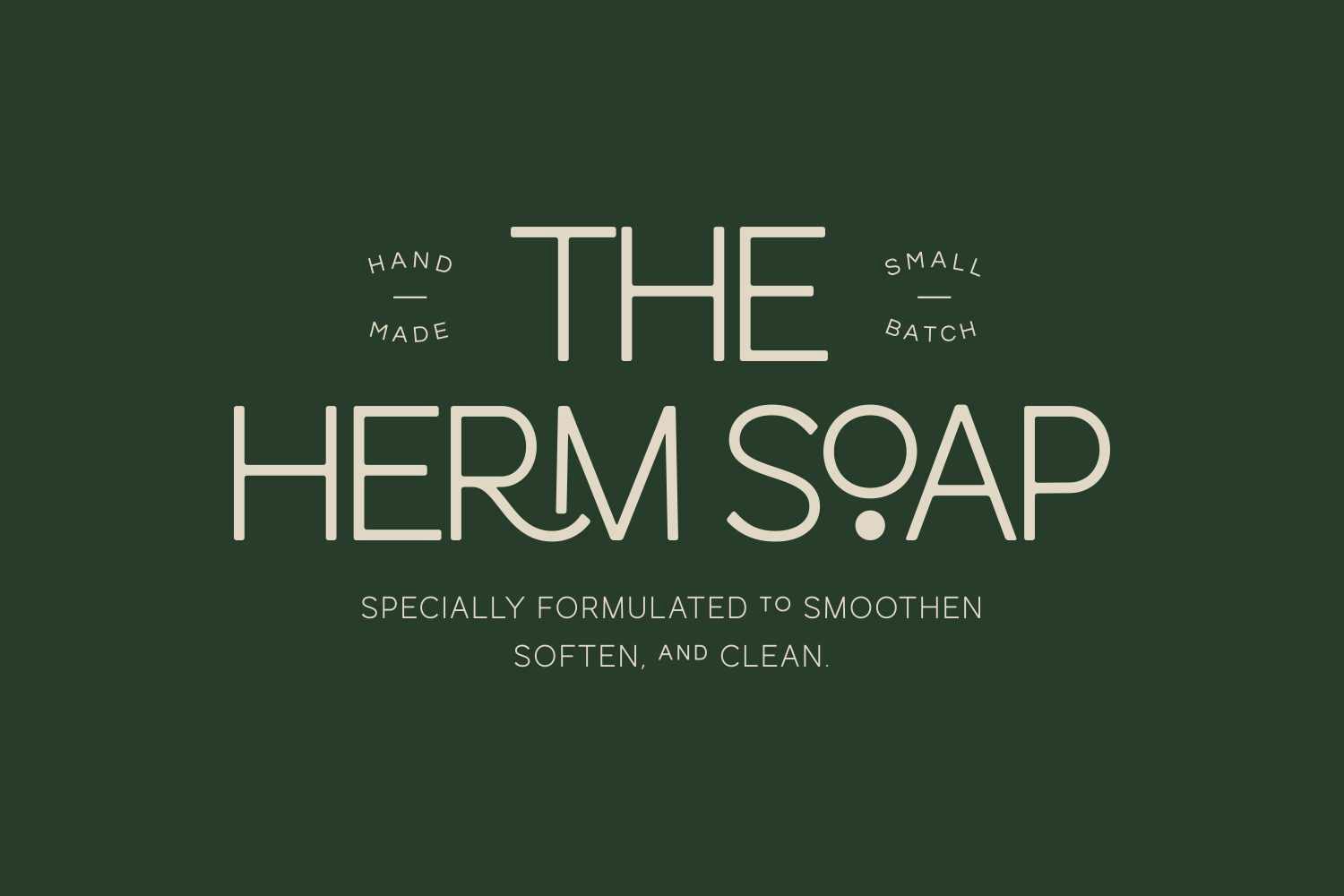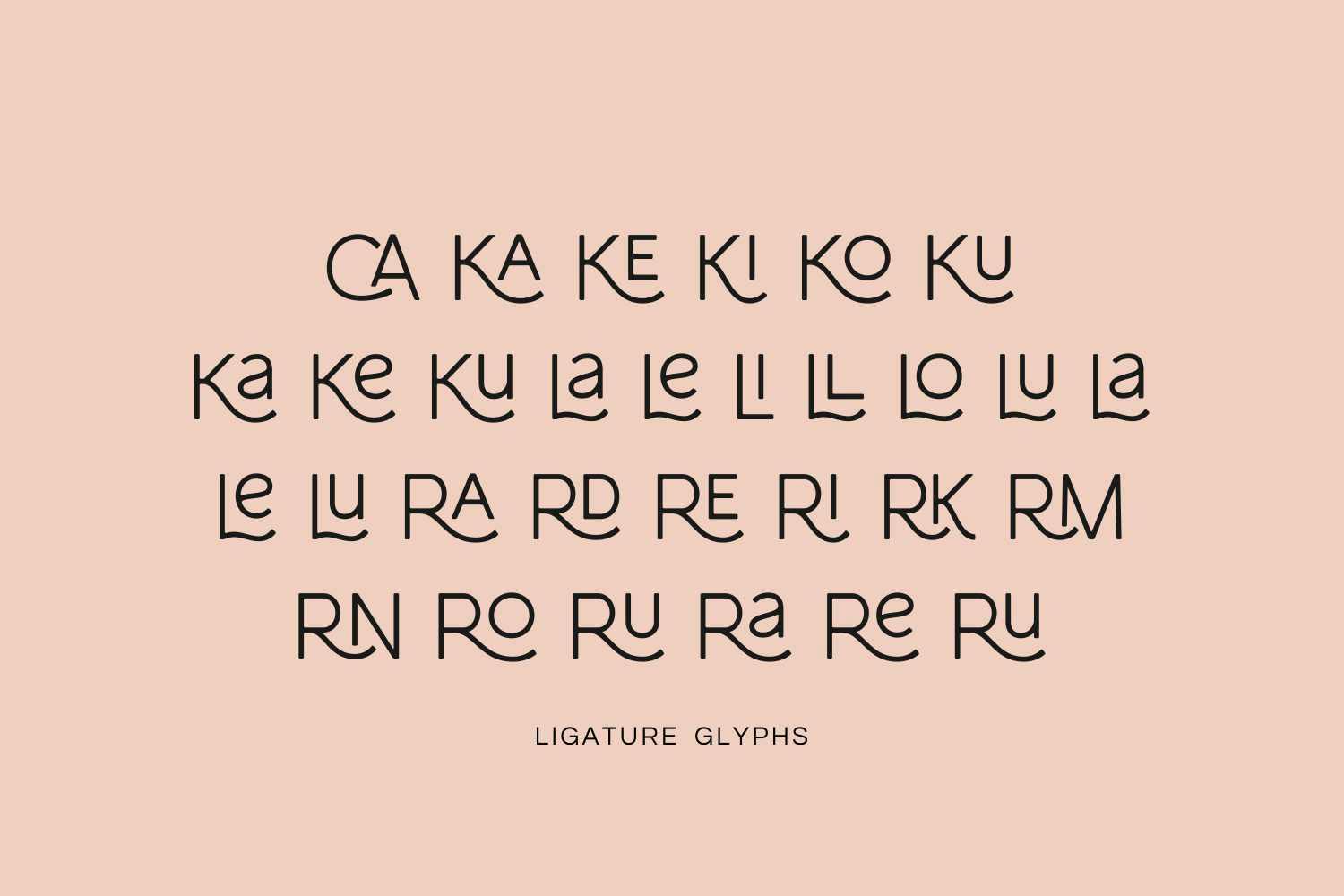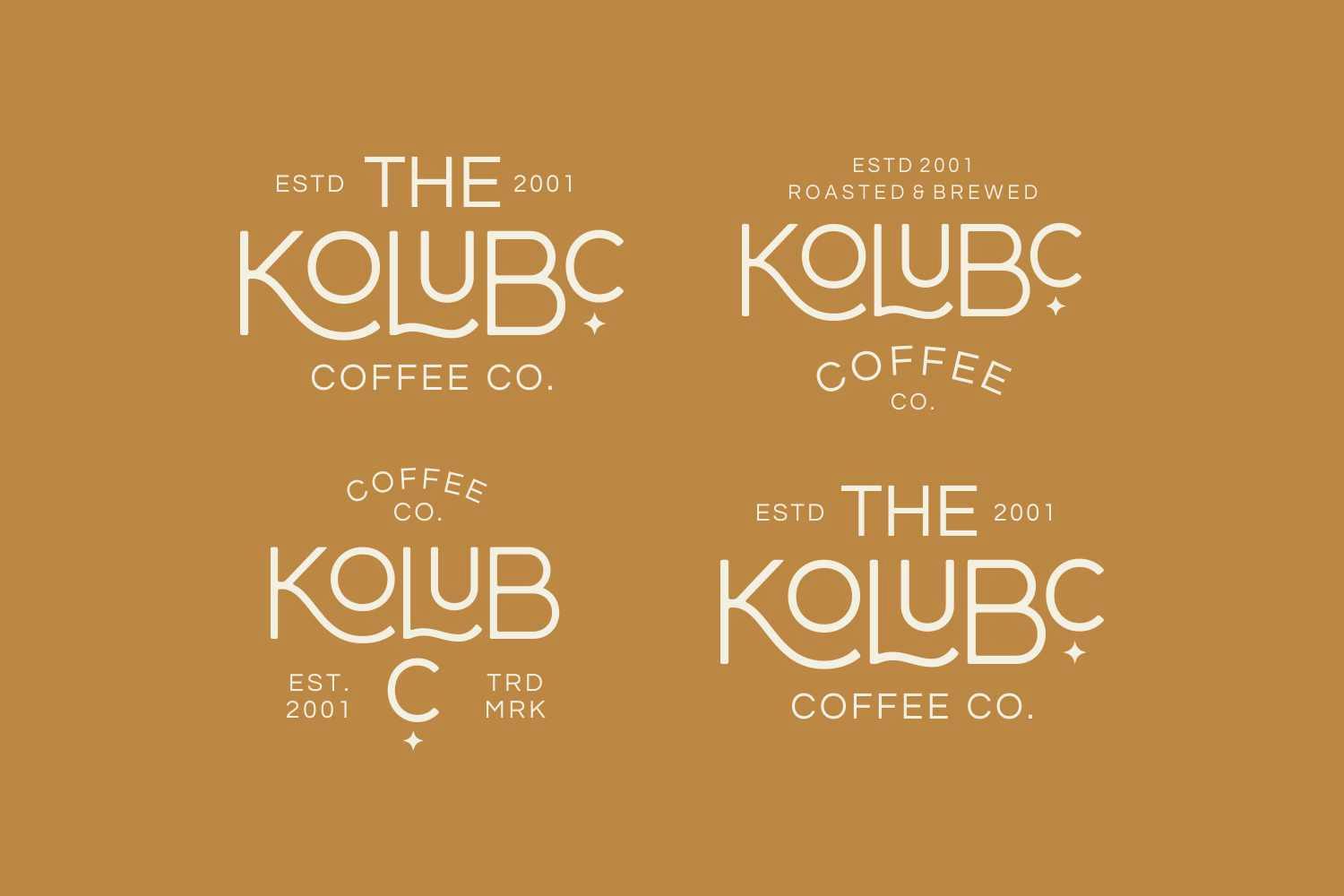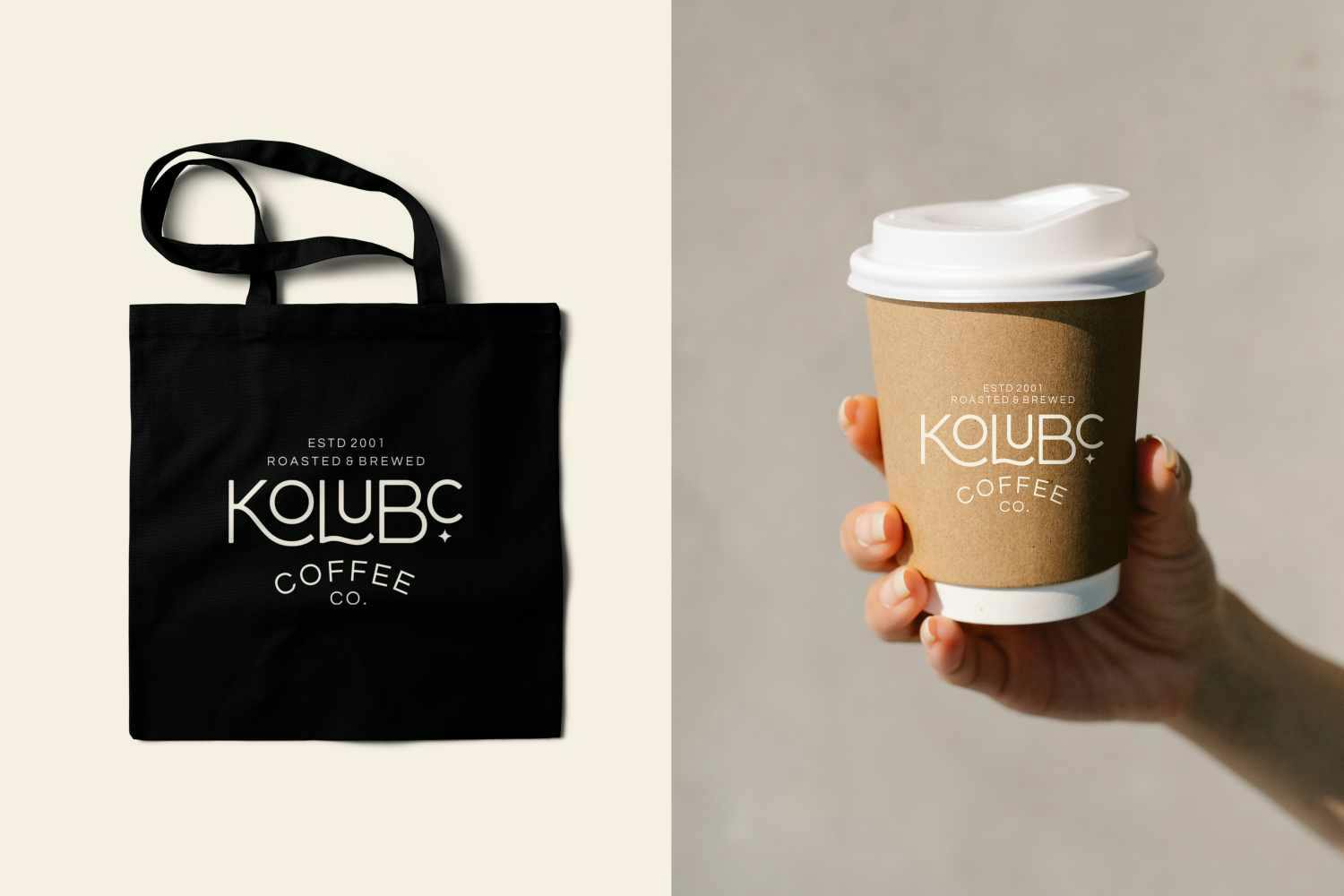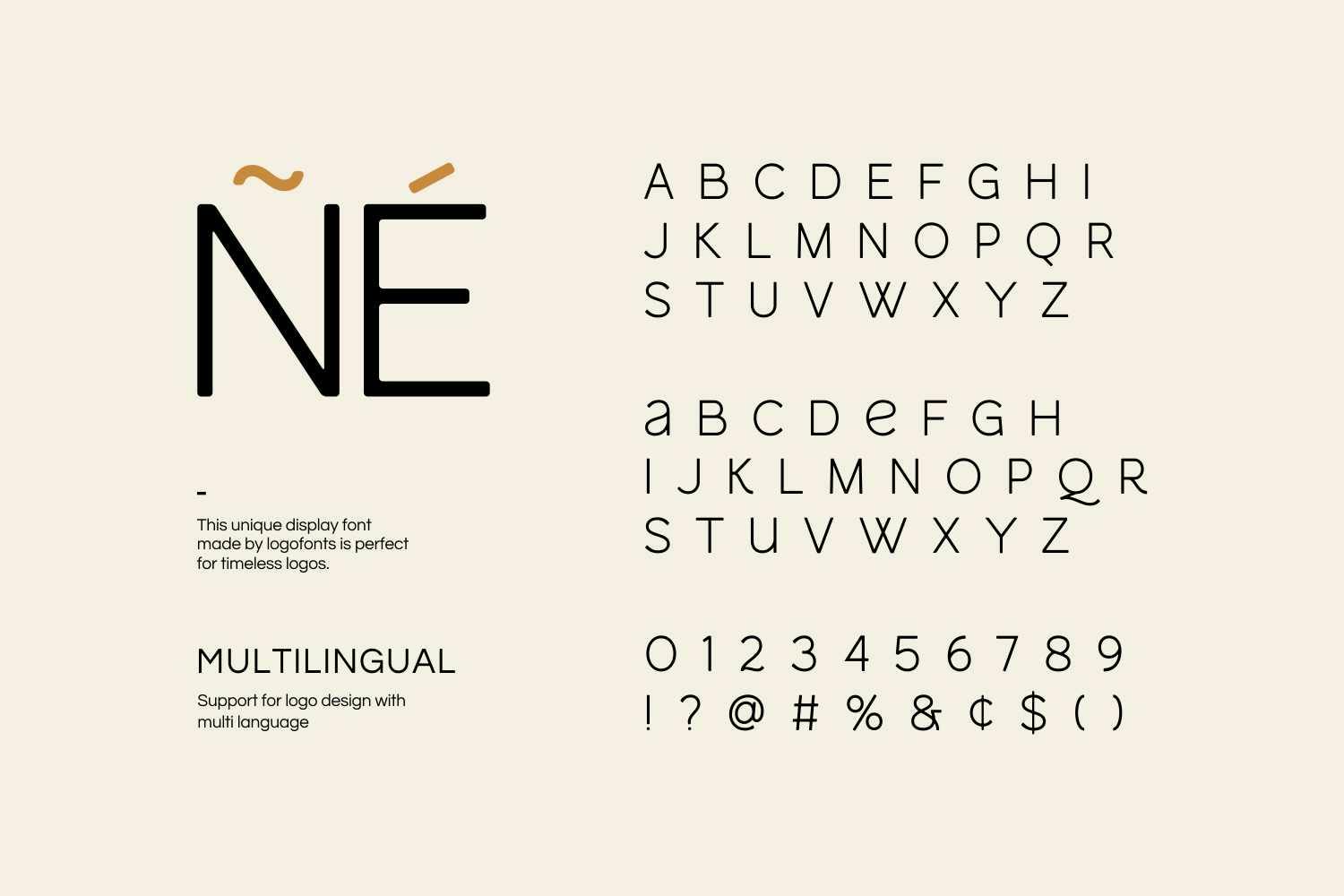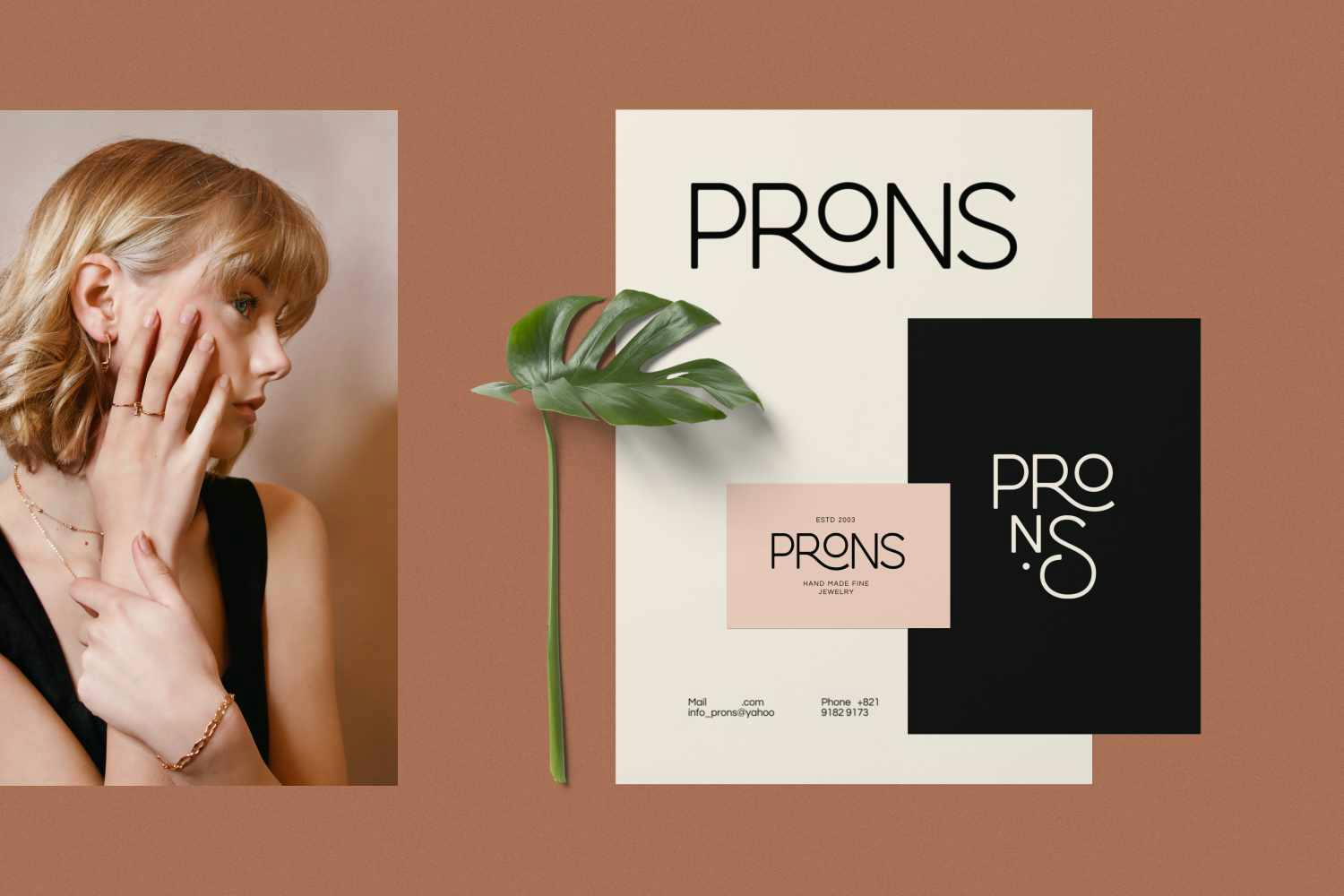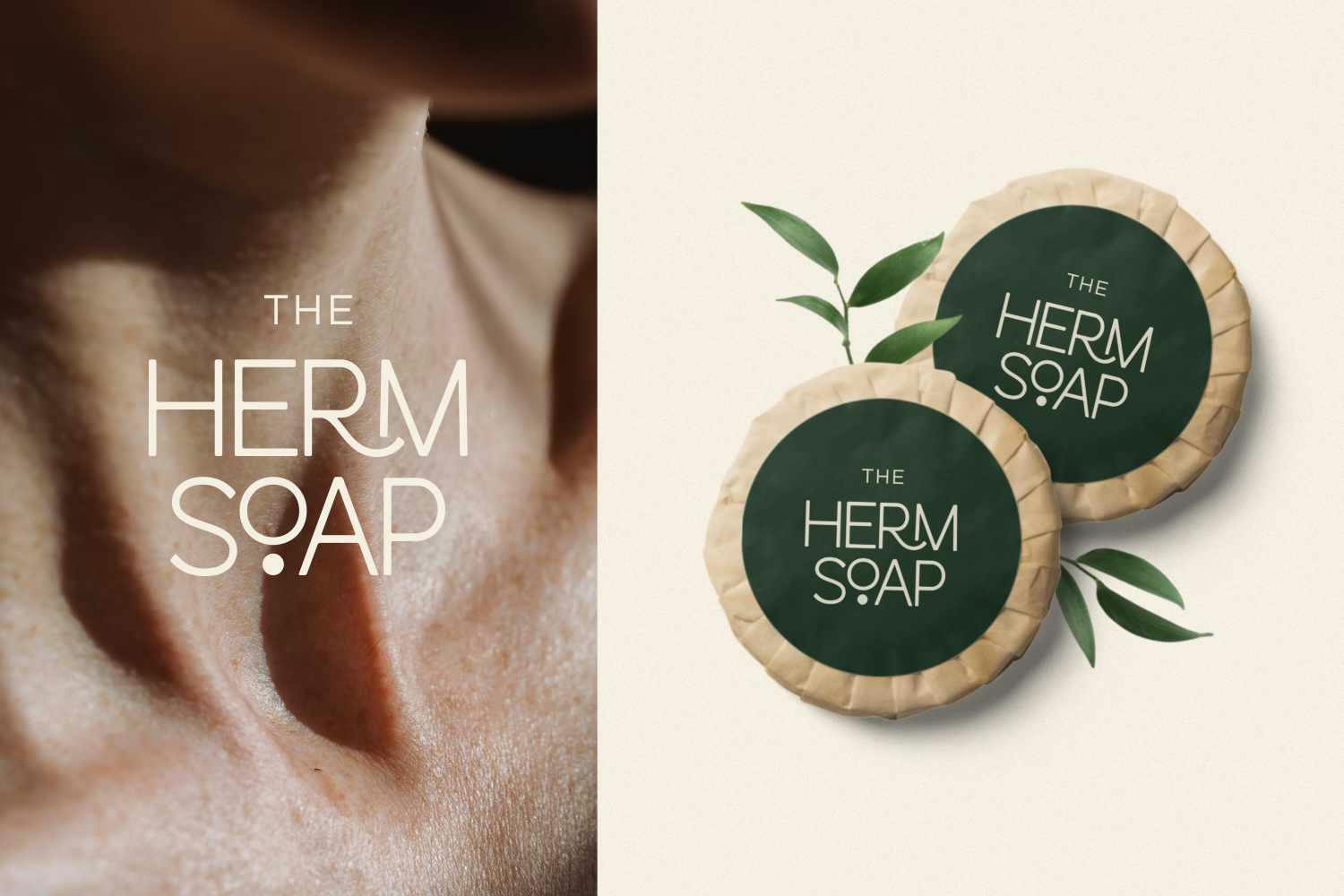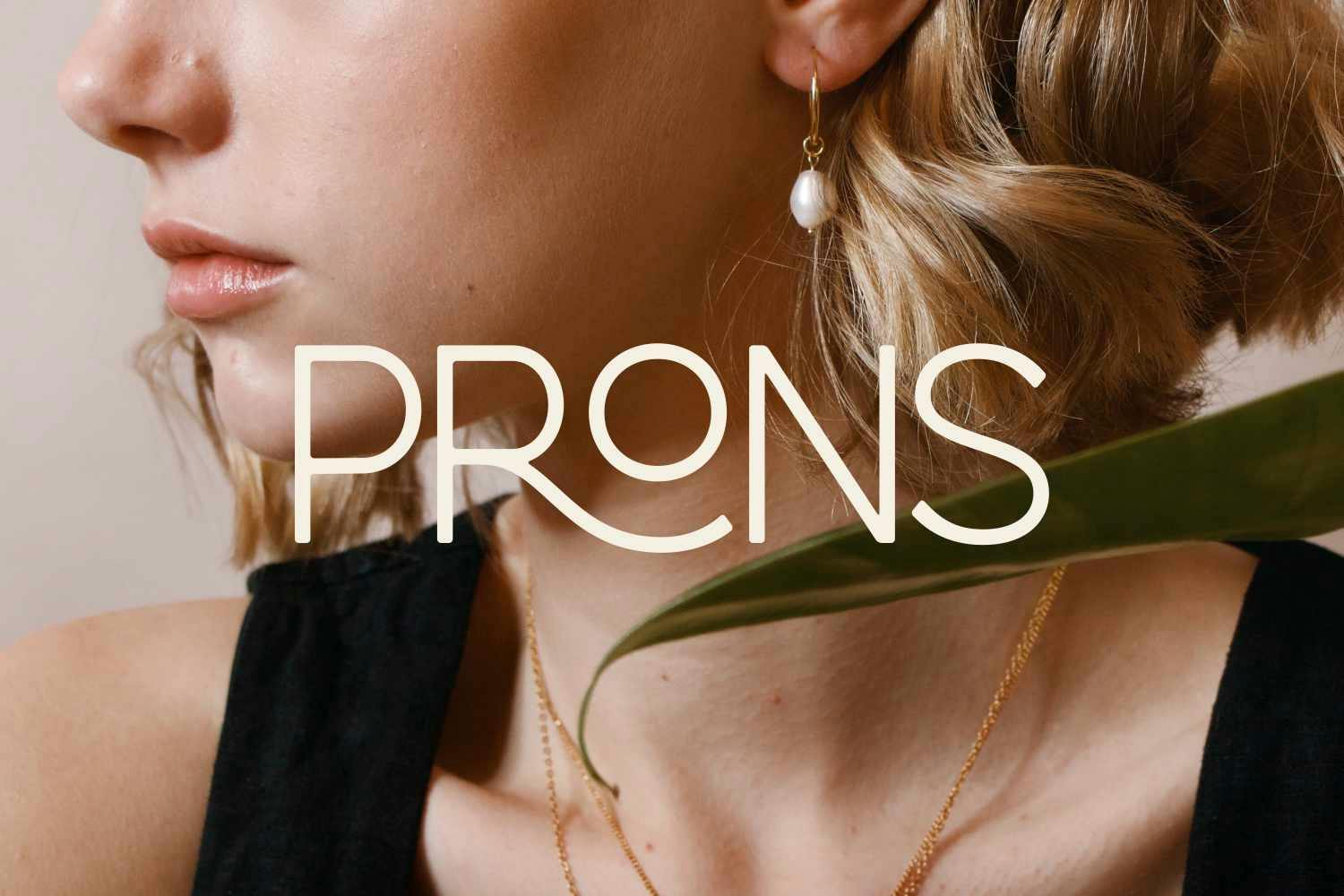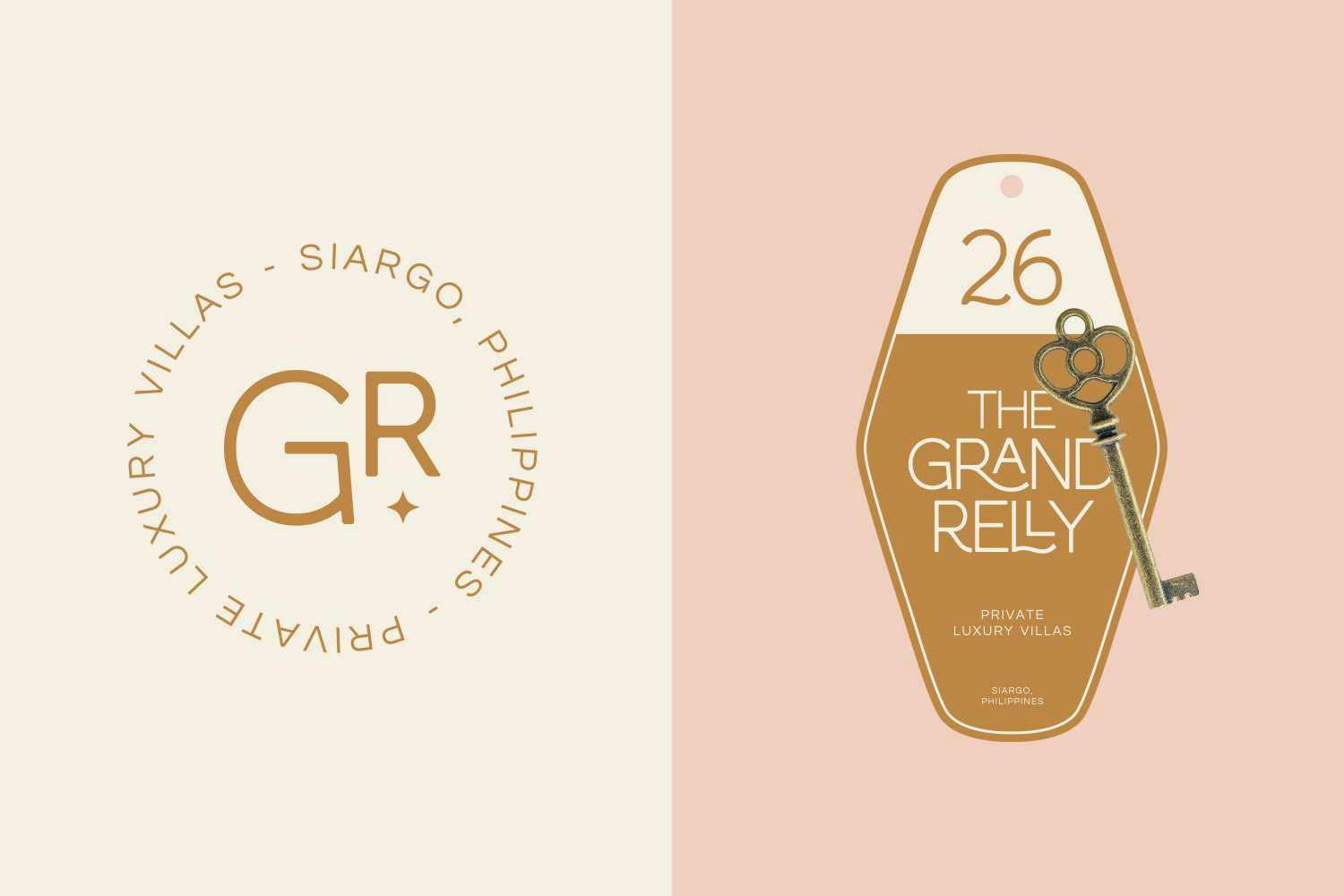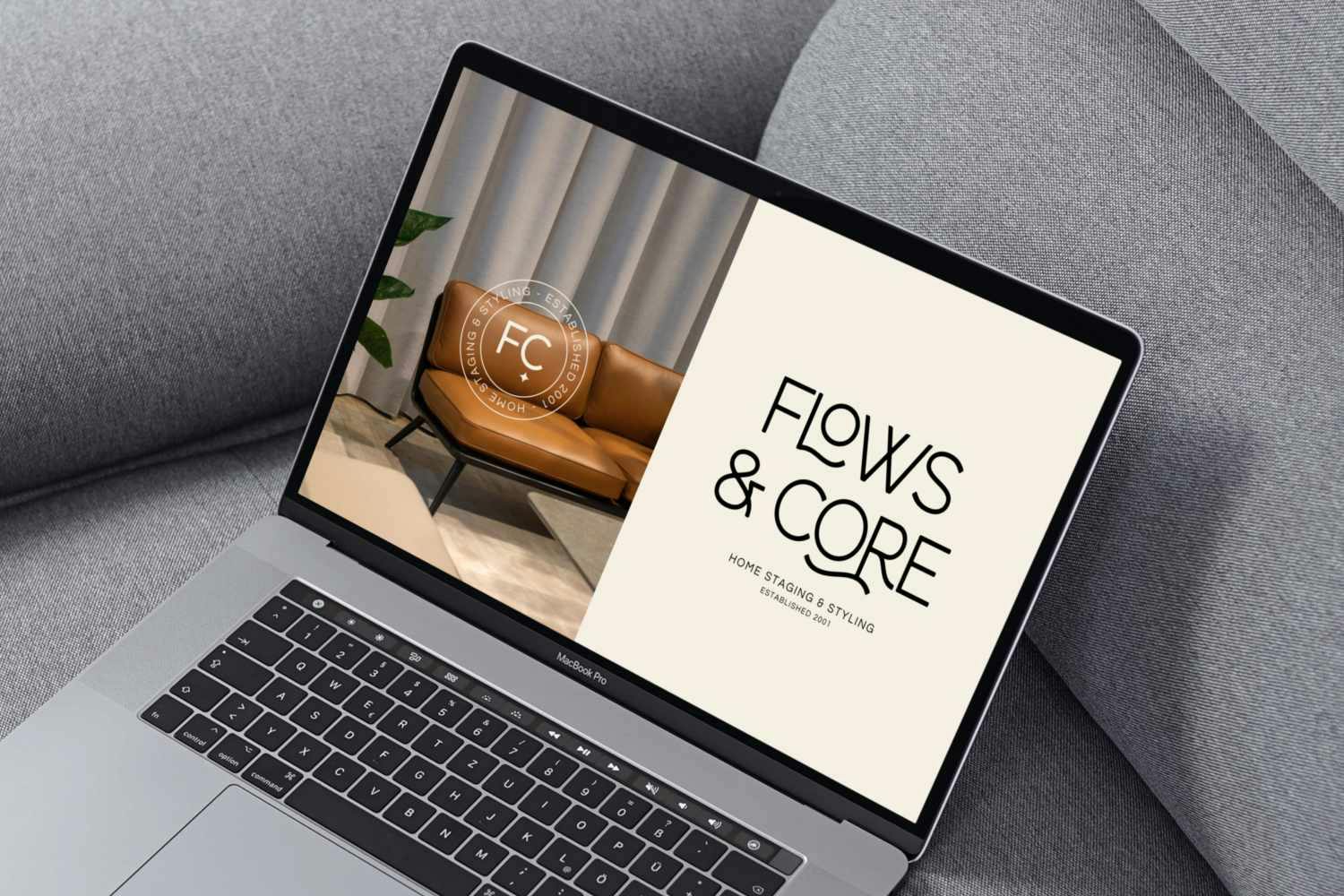
فونت Peosa یک فونت مدرن و sans serif است که برای طراحی لوگو محصولات، پوستر، تیتر، لوگوی کارت، وبسایت، مجله، بستهبندی، لوازمالتحریر و بسیاری موارد دیگر مناسب است. با این فونت به راحتی میتوانید نوع لوگوی خود را ایجاد کنید.
فونت Peosa دارای ویژگی Open Type است که به شما امکان دسترسی به مجموعهای بزرگ از حروف جایگزین منحصر به فرد و بسیاری از ligatureها را میدهد تا فرآیند طراحی شما را سادهتر کند.